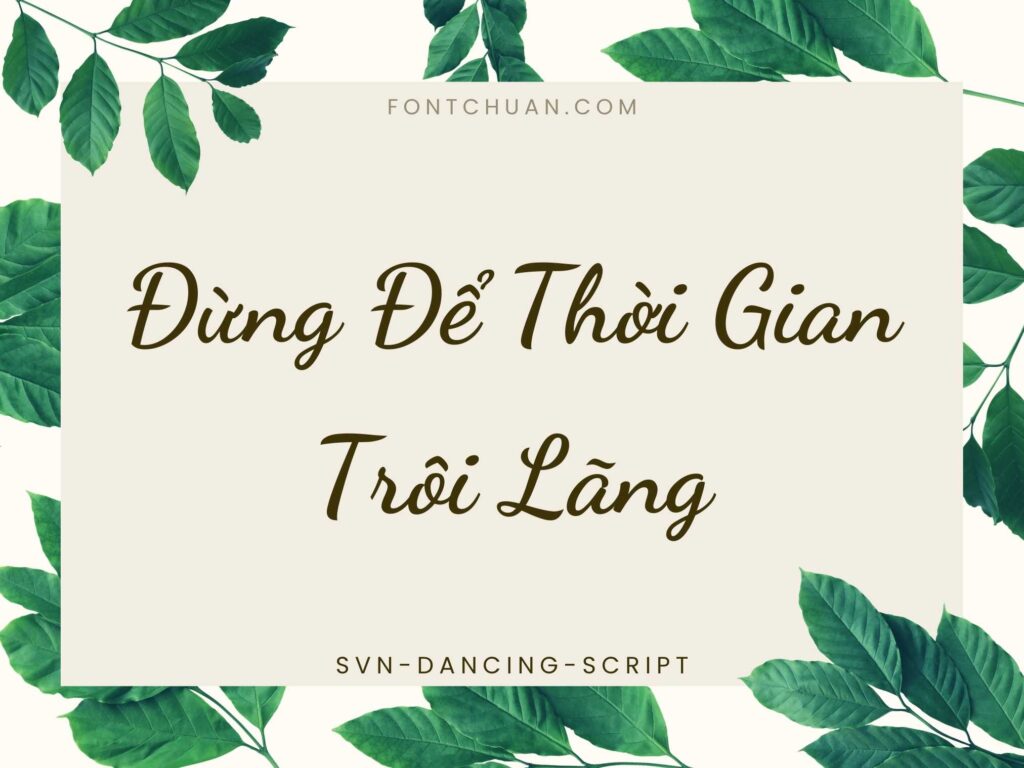
Font SVN Dancing Script Việt Hóa
Tác giả Font: Impallari Type
Dancing Script là một font chữ script sống động và thân thiện, được thiết kế bởi Pablo Impallari. Font này lấy cảm hứng từ các kiểu chữ viết tay phổ biến vào những năm 1950, với các chữ cái nhảy múa và thay đổi kích thước nhẹ nhàng, tạo nên sự linh hoạt và uyển chuyển. Font đã được Việt hóa để hỗ trợ tiếng Việt bởi STYLEno.1 Fonts, đồng thời hỗ trợ nhiều ngôn ngữ khác, giúp mở rộng phạm vi sử dụng trên toàn cầu. Font này được chia sẻ trên Font Tiếng Việt, đáp ứng nhu cầu của người dùng và ứng dụng thực tế vào các dự án thiết kế.
Đặc điểm thiết kế của Dancing Script bao gồm các chữ cái viết tay mềm mại, với các ký tự viết hoa lớn và kéo xuống dưới đường cơ sở, tạo cảm giác vui tươi và gần gũi. Font này phù hợp cho các ứng dụng như thiệp mời, tiêu đề, logo, bài đăng trên mạng xã hội, quảng cáo, bao bì sản phẩm và bất kỳ dự án nào cần đến sự tinh tế của chữ viết tay. Các ngành nghề phù hợp bao gồm quảng cáo, nghệ thuật và thiết kế đồ họa.